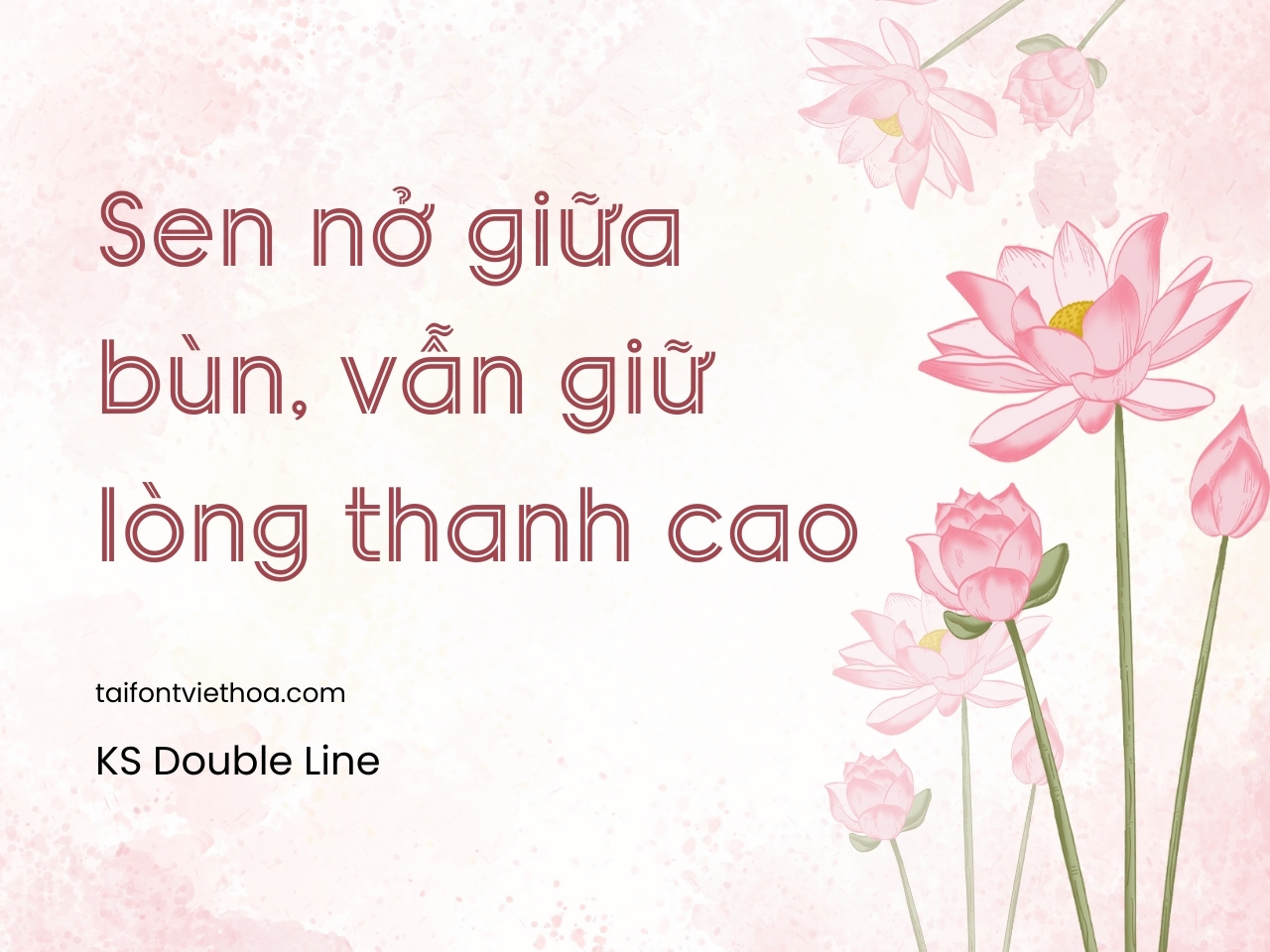
Giới thiệu font Ks Double Line – Thiết kế đường đôi phá cách từ K-Type
Ks Double Line là một kiểu font display hiện đại và phá cách đến từ nhà thiết kế K-Type. Điểm nổi bật của font này là cấu trúc đường đôi chạy song song xuyên suốt các ký tự, tạo nên hiệu ứng thị giác độc đáo và ấn tượng. Font không chỉ gây chú ý ở phần hình thức mà còn dễ nhận diện trong các thiết kế đòi hỏi tính sáng tạo cao. Phiên bản Việt hóa được thực hiện bởi Kiên Sinh, hỗ trợ đầy đủ tiếng Việt và hơn 80 ngôn ngữ quốc tế. Ks Double Line đã được taifontviethoa.com sưu tầm và chọn lọc kỹ lưỡng, nhằm mang đến cho cộng đồng thiết kế một lựa chọn táo bạo, độc lạ, phục vụ tốt các chiến dịch truyền thông và thương hiệu hiện đại.
Phong cách hình học sáng tạo và ứng dụng của Ks Double Line
Font sở hữu các nét chữ cấu trúc hình học, rõ ràng và đối xứng, với hiệu ứng “double line” chạy xuyên suốt, tạo nên chiều sâu và nét phá cách cho thiết kế. Ks Double Line rất phù hợp với các thiết kế logo công nghệ, bao bì sản phẩm sáng tạo, poster lễ hội, banner thương hiệu cá tính, tiêu đề website hoặc app giao diện hiện đại. Font đặc biệt lý tưởng cho các ngành như công nghệ, ẩm thực hiện đại, giáo dục số, truyền thông thương hiệu trẻ, hoặc các sự kiện như Trung thu, Valentine, lễ hội mùa xuân hay các chiến dịch quảng cáo sáng tạo.